5 Peran Font dalam Film, Bagian Krusial dari Branding
Naskah dan akting memang bagian penting dalam sebuah film. Namun, elemen estetik seperti kostum, tata rias, latar, dan properti gak kalah krusialnya. Begitu pula dengan penggunaan typeface atau font. Biasanya font kita temukan di poster, judul, dan kredit, tetapi tak terkecuali properti.
Dulu, font sebatas dipakai untuk tujuan praktikal seperti menampilkan informasi berupa judul dan kredit. Ini mengingat opsi font yang masih terbatas. Namun, seiring berkembangnya zaman, font menjelma jadi simbol yang kompleks untuk sebuah film. Tipe informasi yang mereka tawarkan jadi lebih beragam dan berlapis. Apa saja?
1. Elemen untuk mengidentifikasi genre
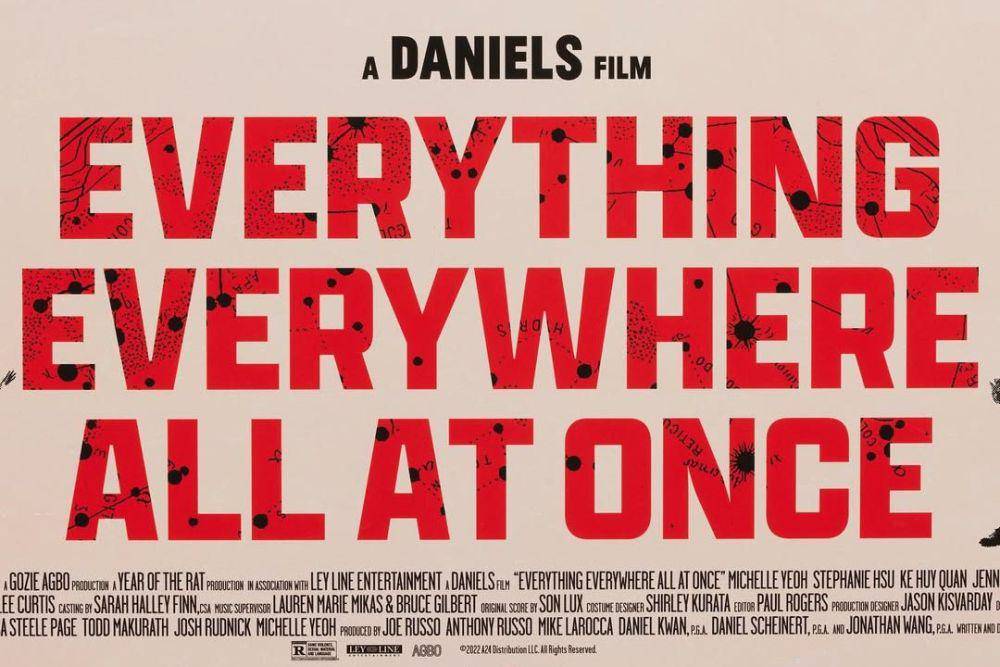
poster film Everything Everywhere All At Once (dok. A24/Everything Everywhere All At Once) Font adalah cara paling mudah untuk menempatkan informasi tentang genre dan gaya film. Contoh paling mudah adalah film-film horor yang biasanya akan memakai font dengan efek darah menetes atau bergaya gothic. Film-film aksi umumnya akan menggunakan font yang bergaris tegas dan tebal. Sementara, film-film romantis kerap memakai typeface dengan kait yang memberikan efek feminin dan elegan.
Di sisi lain, film-film animasi sering dikaitkan dengan font-font bernuansa playful dan cair. Tentu, ini bukan pakem yang harus dituruti. Ada kalanya film horor menggunakan font minimalis dan bold, terutama yang memang dibuat dengan konsep minimalis modern seperti sinema-sinema horor independen kontemporer macam Longlegs (2024) dan The Killing of the Sacred Deer (2017).
2. Bagian integral dari sebuah film
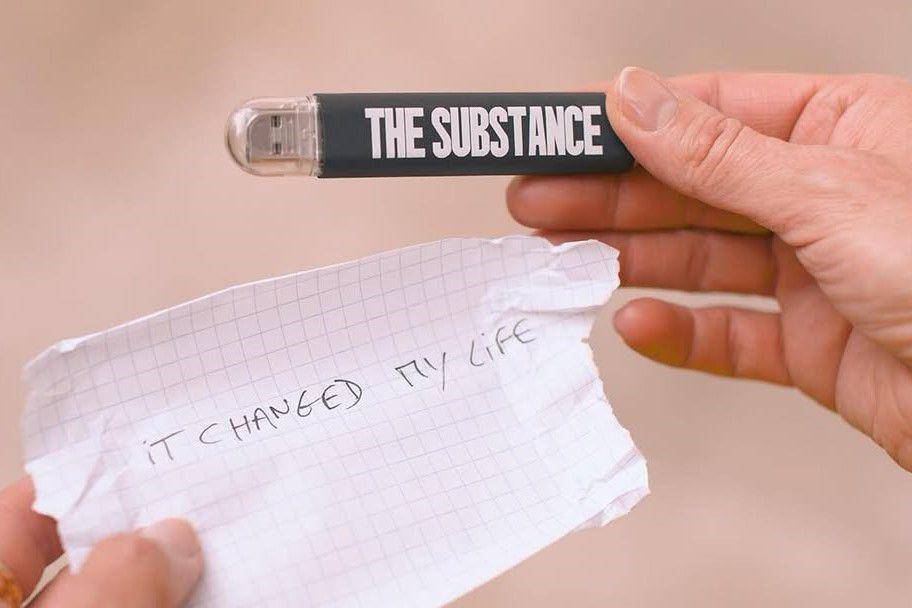
cuplikan film The Substance (dok. MUBI/The Substance) Beberapa sineas juga tampak menyertakan font sebagai bagian integral dari film secara keseluruhan. Contoh termudahnya adalah The Substance (2024) yang font judulnya juga bisa kamu temukan dalam berbagai properti film. Coralie Fargeat, sang sutradara bekerja sama dengan studio desain asal Prancis, Fugu Production untuk membuat custom font tersebut.
Font ini sebenarnya mirip dengan typeface gratis di Google Fonts yang bernama Anton. Namun, tampak ada beberapa modifikasi dan penyesuaian di sana-sini untuk menghasilkan sebuah typeface baru yang khas. Belum banyak film yang menempatkan peran font secara terpadu seperti ini.
3. Identitas sebuah brand dan franchise-nya
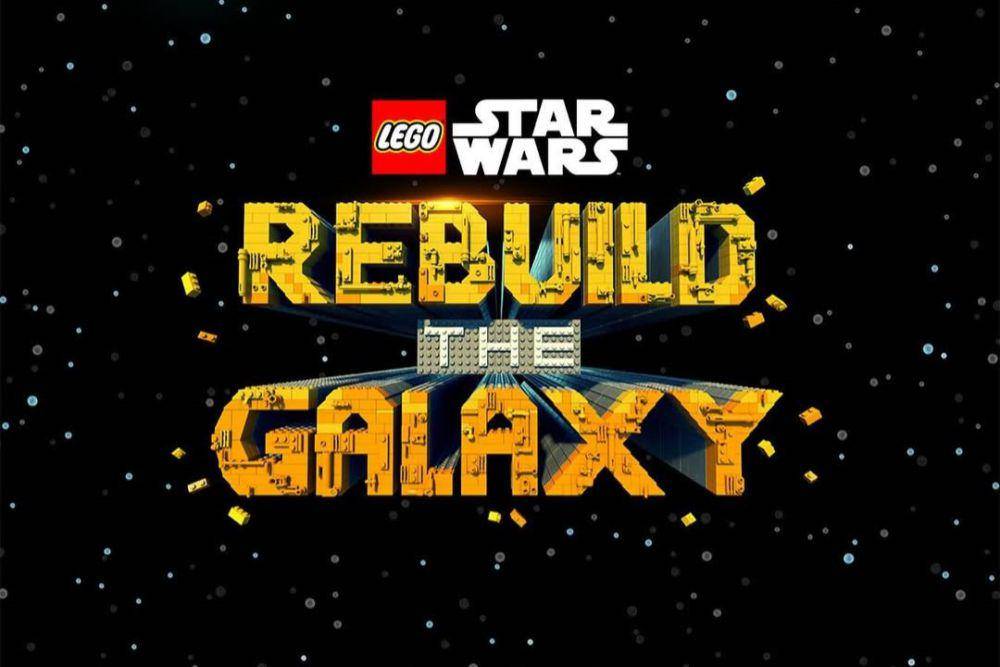
poster serial Lego Star Wars: Rebuild the Galaxy (dok. Lucasfilm/Lego Star Wars: Rebuild the Galaxy) Font juga bisa dijadikan identitas sebuah brand atau perusahaan tertentu. Star Wars beserta font dan slogannya sudah didaftarkan sebagai merek dagang yang sah sehingga tak bisa digunakan sembarangan oleh pihak lain. Begitu pula dengan film Barbie (2023), terafiliasi dengan Mattel dan akhirnya menggunakan typeface sama dengan yang biasa dipakai perusahaan tersebut untuk kemasan produk boneka mereka. Hal serupa bisa kamu temukan dalam film Harry Potter, Godfather, dan Indiana Jones.
Ada yang jelas dan tak bisa diubah-ubah, ada pula brand yang menempatkan signatur khas mereka dengan cara yang lebih tak kentara. Distributor film A24 dan NEON misalnya. A24 sering menggunakan typeface minimalis modern, termasuk untuk film horor. Ini sesuai dengan perusahaan mereka yang identik dengan film-film independen minimalis. Sementara, NEON sering membuat poster berwarna mencolok atau memberikan efek menyala seperti lampu neon pada typeface.
4. Ciri khas sutradara
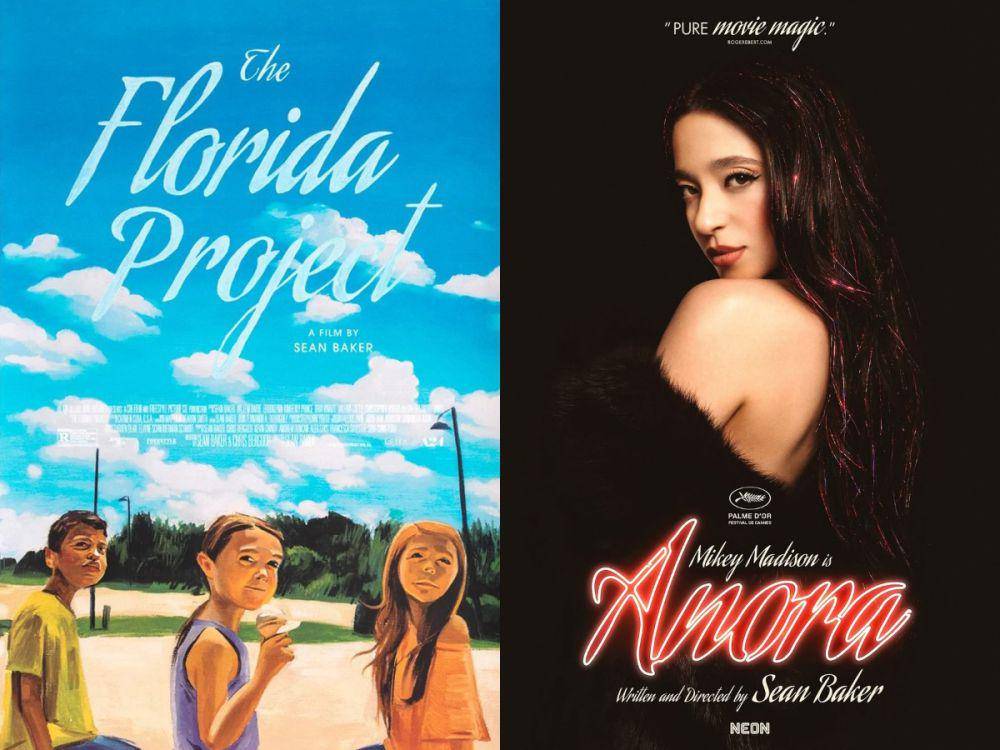
poster film The Florida Project dan Anora (dok. A24/The Florida Project | dok. NEON/Anora) Font juga bisa jadi ciri khas sutradara, lho. Sean Baker misalnya sudah beberapa kali menggunakan font gratis bernama Aguafina Script Pro yang dikembangkan studio desain asal Argentina, Sudtipos. Font itu ia pakai sejak film Tangerine (2015), dilanjut The Florida Project (2017), Red Rocket (2021), dan terbaru Anora (2024). Menariknya, keempat film itu dirilisnya lewat distributor yang berbeda-beda.
Sutradara lain yang sering memakai font serupa untuk karya sinematik mereka adalah James Cameron (Papyrus) dan Ingmar Bergman (Florida). Tentu tidak semua sutradara punya privilese dan idealisme ini, lagipula konsistensi penggunaan font tidak berbanding lurus dengan konsistensi berkarya. Yorgos Lanthimos beberapa kali mengganti typeface, tetapi gaya sinematiknya tetap tampak jelas.
5. Menunjukkan referensi kultural
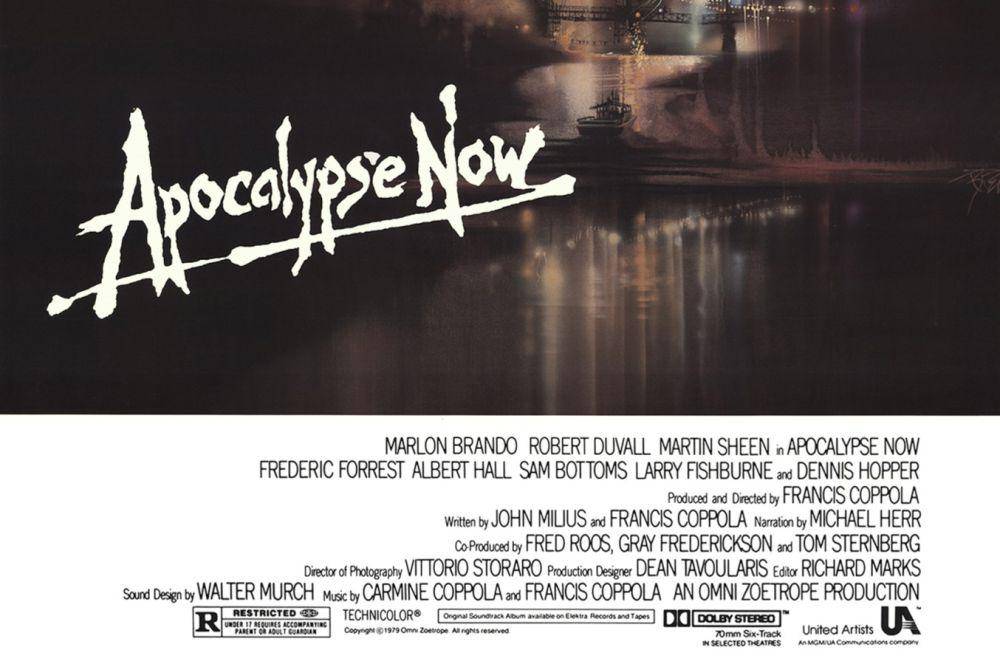
poster film Apocalypse Now (dok. American Zoetrope/Apocalypse Now) Beberapa film bisa saja menggunakan referensi kultural untuk memilih font. Apocalypse Now, Prince of Persia, Aladdin, sampai Moana adalah beberapa contohnya. Meski umum dilakukan, belakangan penggunaan budaya sebagai rujukan mulai dihindari. Ini karena dalam praktiknya, kebanyakan masih bertumpu pada stereotip dan stigma ketimbang representasi yang proporsional. Prince of Persia misalnya dikritik karena sarat whitewashing (merekrut aktor kulit putih untuk memerankan karakter etnik tertentu) dan adegan-adegan stereotipikal.
Berkaca dari pengalaman itu, sepertinya studio film memilih untuk meninggalkan opsi ini saat memutuskan font yang akan dipakai. Film-film dengan referensi kultural kental saja memilih untuk pakai font netral. Lihat saja Crazy Rich Asians (2018) dan The Farewell (2019). Serial Reservation Dogs (2021) yang berkutat di sebuah kawasan reservasi khusus penduduk pribumi pun memilih font bernuansa grafiti. Artinya mereka memilih anak muda sebagai titik beratnya, ketimbang budaya.
Seperti yang ditulis Lei Wang dalam jurnal berjudul The Art of Font Design in Movie Posters, dari yang hanya mengemban informasi sederhana dalam film, font kini adalah sebuah elemen seni independen yang menyimpan satu set informasi. Ia bisa berdiri sendiri sebagai identitas perusahaan, tokoh, hingga genre.